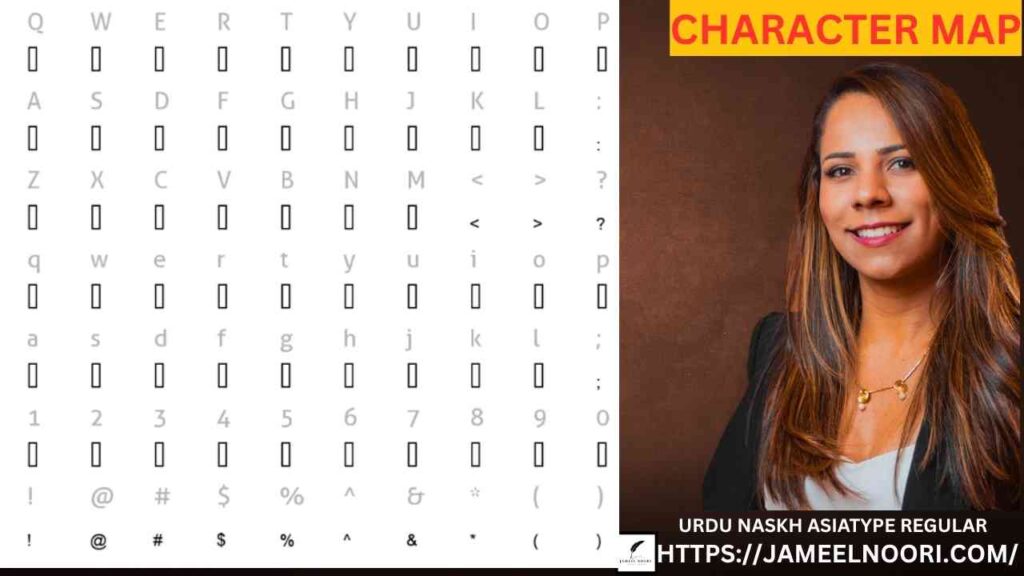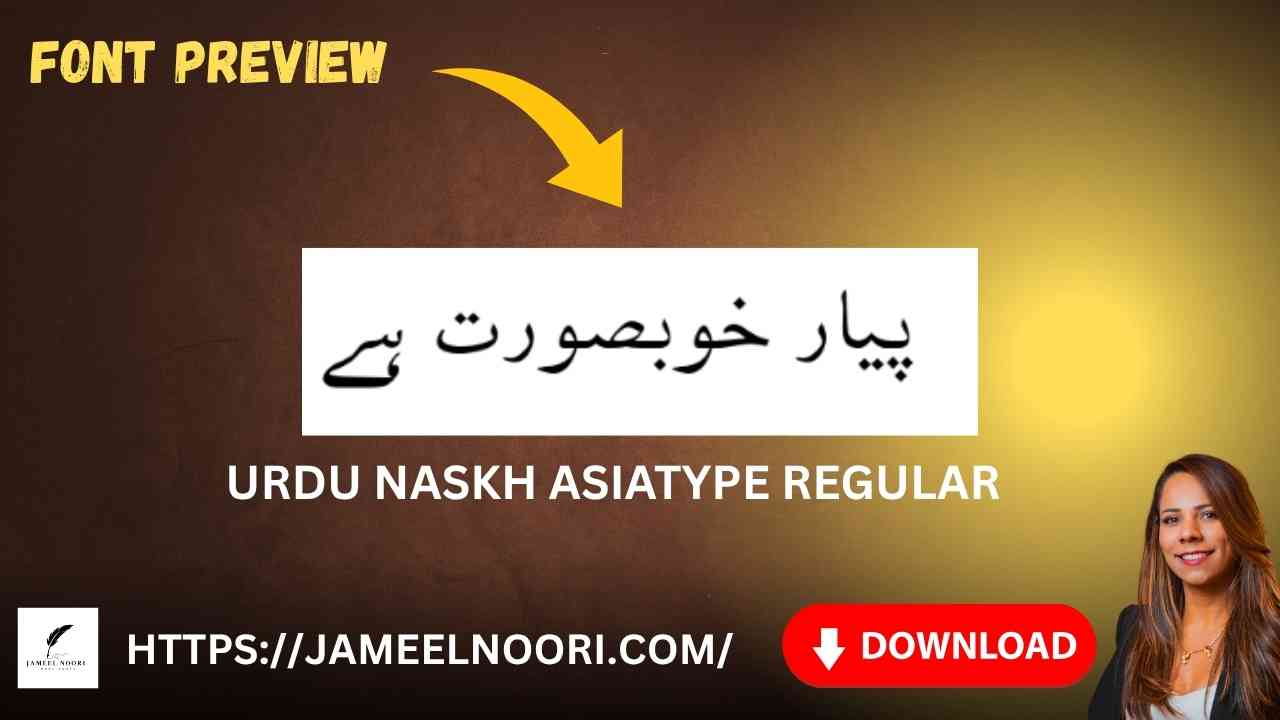
Agar aap Urdu typing, graphic designing ya publishing ka kaam karte hain, to aap ke liye Download Urdu font Urdu Naskh Asiatype Regular ek zaroori font ban sakta hai. Yeh font OpenType format me available hai aur isay ab tak 6789 dafa download kiya ja chuka hai. Iski readability aur naskh-style ki wajah se yeh Pakistan ke designers ka favorite font ban gaya hai.
Download Urdu font Urdu Naskh Asiatype Regular aik elegant aur readable Urdu font hai jo kisi bhi digital ya print media project me professional look deta hai. Is font ka naskh-style typography Pakistan aur India dono me widely accept kiya jata hai.
Key Reasons to Choose This Font:
- Stylish aur readable Urdu typography
- Best for headlines, body text aur graphic design
- High-quality stroke & balance
�� Where You Can Use Urdu Naskh Asiatype Regular Font
Aap is Download Urdu font Urdu Naskh Asiatype Regular ko kai jagah use kar saktay hain:
- Urdu newspaper layout
- Book composition
- Website Urdu content
- YouTube Urdu thumbnails
- Social media Urdu quotes
Conclusion: Why Download Urdu font Urdu Naskh Asiatype Regular?
Agar aap Urdu me readability, professionalism aur compatibility chahtay hain to Download Urdu font Urdu Naskh Asiatype Regular is your best choice. Yeh font Pakistan ke top designers ka favorite hai aur har tarah ke Urdu projects ke liye perfect hai. Isay download karein aur apne projects ko ek naya look dein!